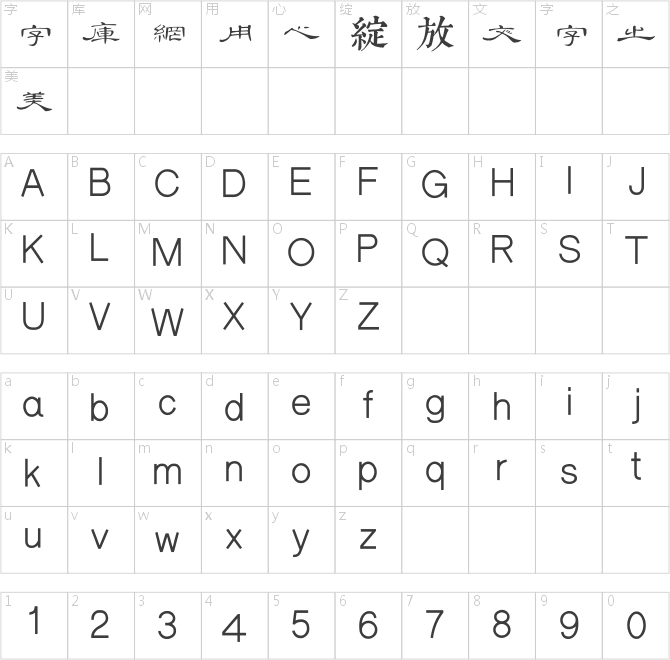
字体名称: 邯郸席夔隶书千
邯郸席夔隶书千字文
邯郸席夔隶书千字文字体下载邯郸(清)席夔隶书千字文
席夔,字梧川,唐朝书法家,诗人。贞元十年进士及第,十二年博学宏词及第。
邯郸席夔隶书千字文字体邯郸(清)席夔隶书千字文字库是一款让人赏心悦目、百看不厌的中文字体,适合各类广告和产品包装设计应用,字体大小6.45MB,格式为ttf字体,上传用户是邯郸字库,作者/版权方为韩绍杰